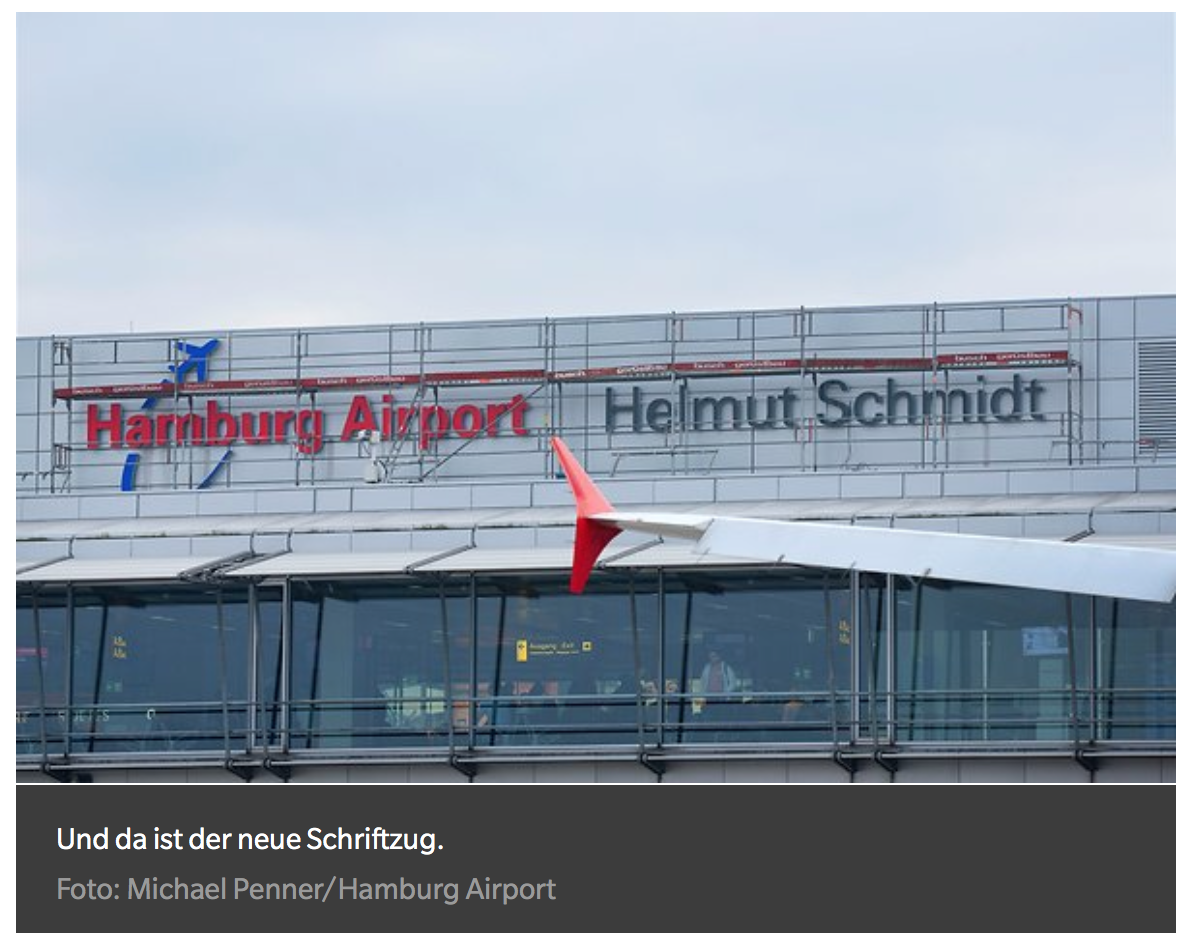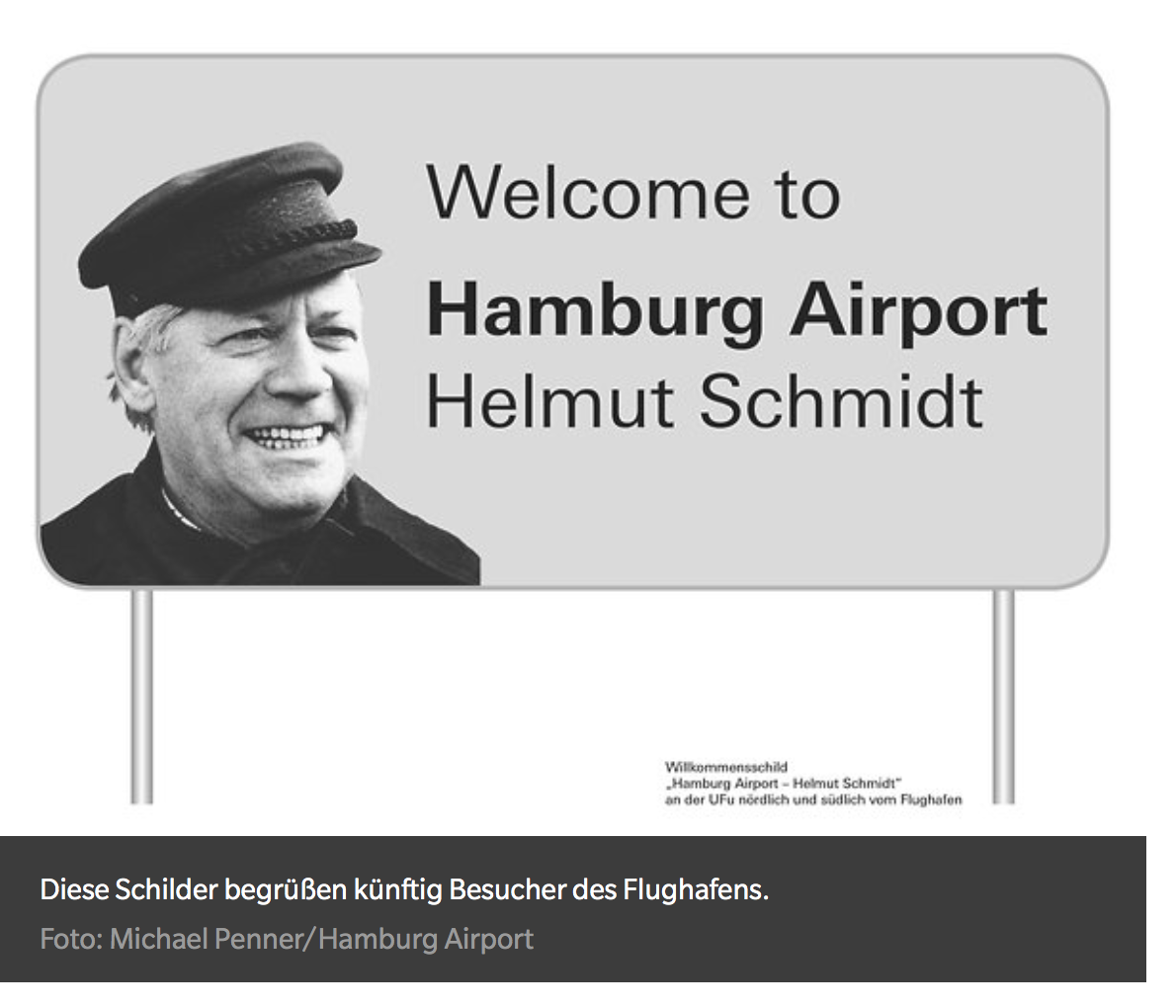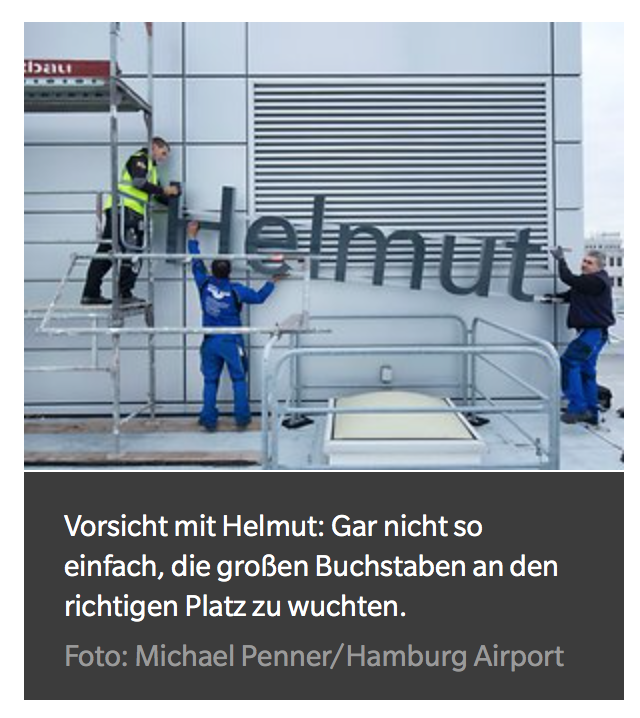
Hmm, also auf Englisch klingt das so ziemlich holprig. Mal sehen, wie konsequent das benutzt wird.
Och, Flughäfen heißen ja häufig irgendwie sperrig. Der in Johannesburg hieß zum Beispiel erst Jan Smuts Intermational Airport, jetzt heiß er Oliver Tambo Intermational Airport (Der Wechsel hat geschichtliche Gründe). Alles eine Sache der Gewöhnung. Und Schmidt Schnauze hat sicherlich nichts dagegen, ein bisschen sperrig zu sein.
Die meisten Hamburger werden vermutlich weiterhin »Fuhlsbüttel« zum Flughafen sagen, so wie sie »Volksparkstadion« zum Volksparkstadion sagen, auch wenn es zwischendurch mal gar nicht so heißt.  ;-)
Schon klar. Es ging mir um die Wortstellung. Helmut Schmidt (International) Airport (of/in/at Hamburg) wäre die übliche Variante. Aber Hamburg Airport Helmut Schmidt geht auf keinen Fall. Das würden viele Englischsprecher gar nicht als einen Eigennamen wahrnehmen, da es schlicht nicht üblich ist, Bezeichnungen ohne Präposition hinter den Gattungsbegriff zu stellen.
Och, da wollte vermutlich einfach ein oberdesigniger Gestalter unbedingt so einen schönen Wechsel haben zwischen book, bold und book. Sch***  auf den Inhalt, auf die Form kommt es schließlich an! ;-)
Wenn ich mir an der Fassade den Farbwechsel, Schnittwechsel und Abstand zwischen Airport und Helmut anschau, käme ich eh nie drauf, dass die beiden Begriffe irgendwas miteinander zu tun haben sollen. Und das Willkommensschild? Na ja, da wird halt Helmut Schmidt am Hamburg Airport begrüßt. Nette Geste eigentlich, aber ein wenig zu spät.